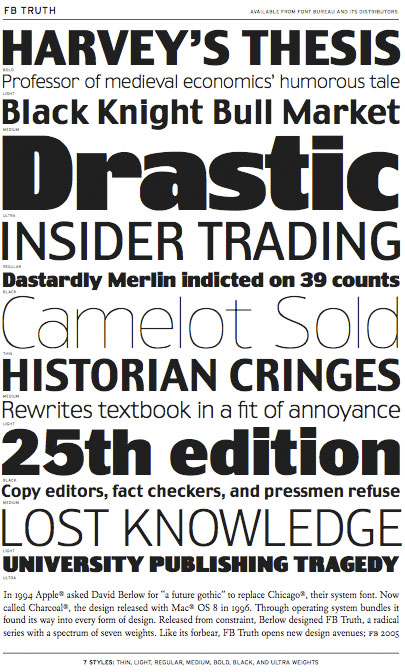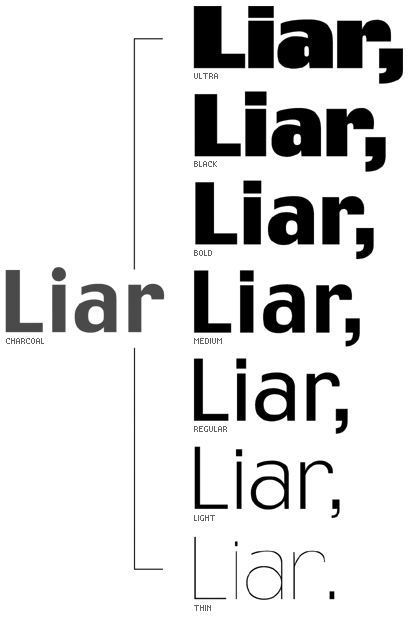
FontBureau bringt die wahre Schrift»Truth« heißt eine neue Schriftfamilie von David
Berlow (The FontBureau, Inc). Die ganze Wahrheit: Es ist die vektorisierte
und ausgebaute Form einer Macintosh-Menüschrift, die 1996 die veraltete
Chicago ablöste. Berlow entwickelte sie als TrueType-Schrift
Chaircoal, besser lesbar und etwas enger laufend als die alte Chicago.
Jetzt hat er aus der Grundform eine komplette Familie mit sieben
Im Jahre 1994 fragte Apple bei David Berlow nach, ob er nicht eine moderne
Gothic entwerfen könne, die den unpraktischen fetten System-Font Chicago
ablösen soll. Zwei Jahre später, mit Erscheinen von System 8.0,
tauchte diese Schrift mit dem Namen Chaircoal erstmals in der
Macintosh-Menüleiste auf. Gleichzeitig brach Apple erstmals mit der
Tradition, seinen Systemschriften Städtenamen zu geben (Chicago, Geneva,
Athens, Cairo,
...).
![]() Nun hat Berlow auf der Basis von Chaircoal die neue Schriftfamilie Truth entwickelt, eine markante Gothic mit starkem Kontrast. Das Chaircoal-Original definierte er als Medium, woraus er jeweils drei leichtere und drei fettere Schnitte extrapolierte. Die Familie besteht somit aus 7 Mitgliedern; Italics sind noch nicht verfügbar. ![]() Schriftmuster als PDF Hinweis: Die neue Truth ist bei FontShop noch nicht im Download lieferbar. Bitte rufen Sie an, um eine Bestellung mit Lieferung per UPS aufzugeben 030 69596-333. Herausgegeben: Mo - Oktober 10, 2005 at 01:56 nachm. | |